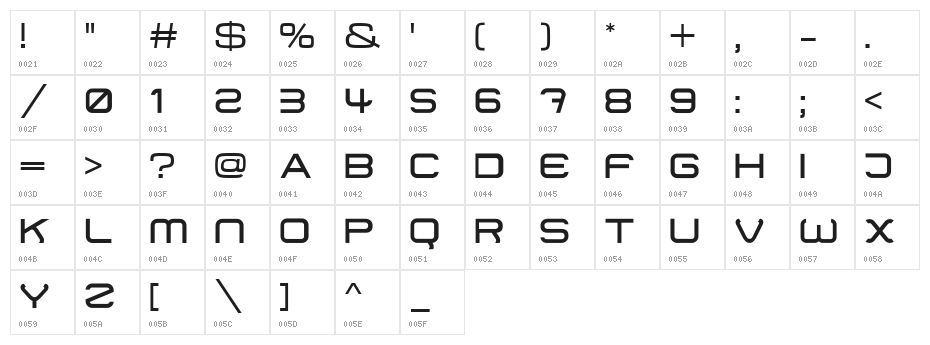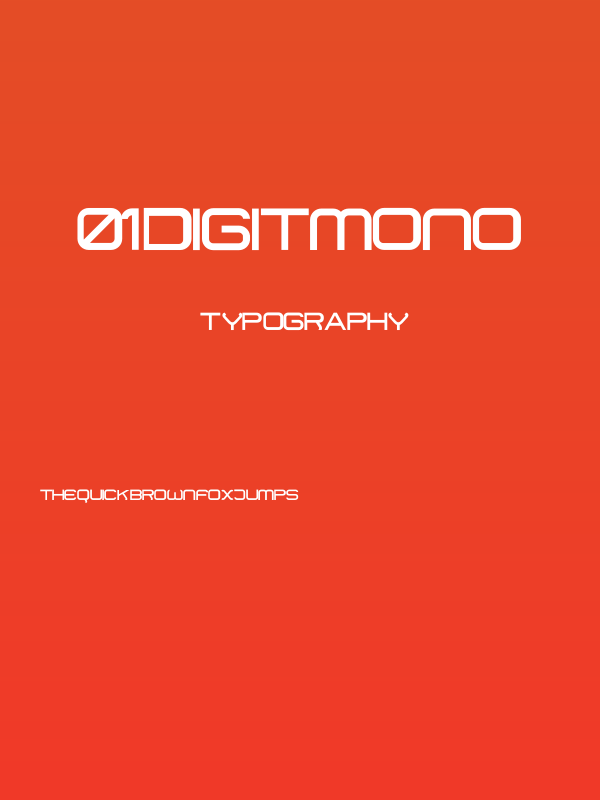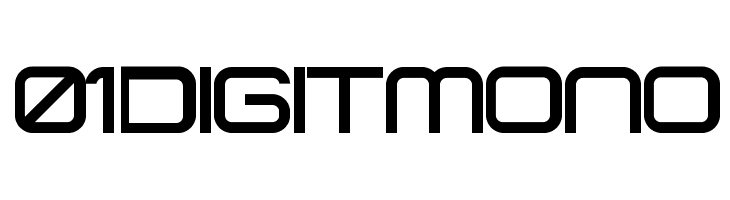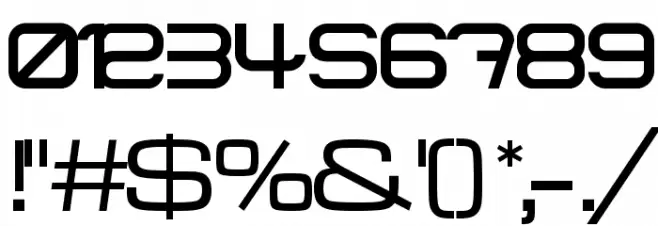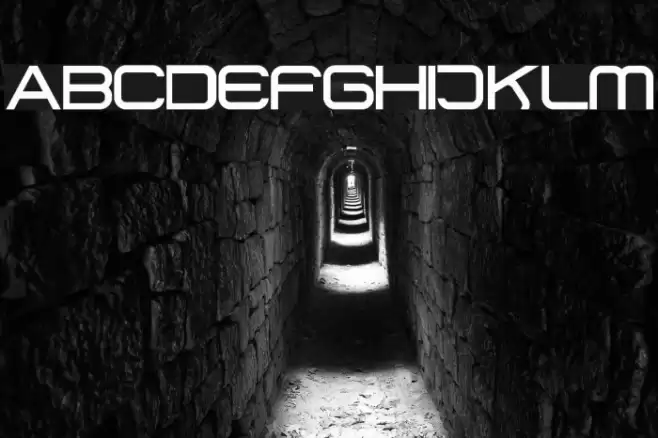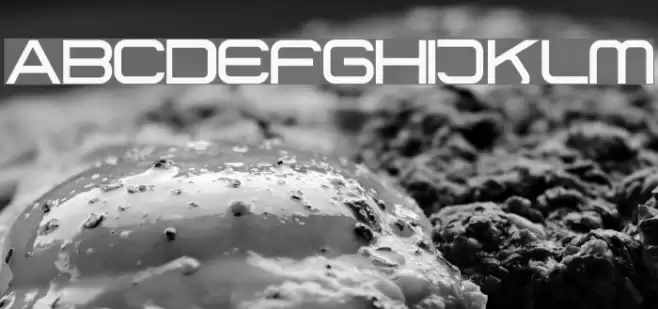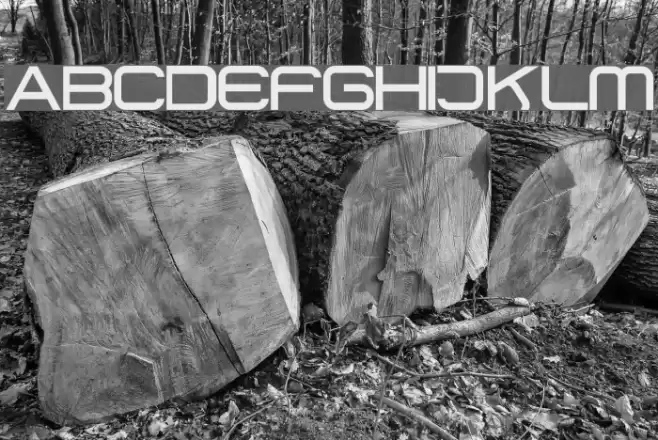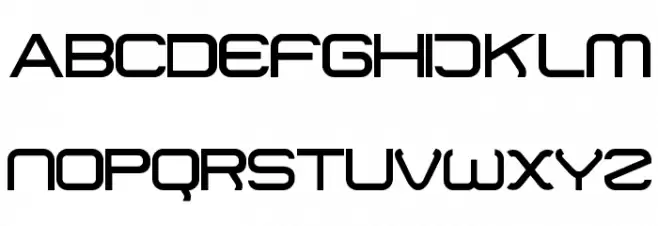
01 DigitMono Font
| حالة الاستخدام | Digital displays, technical documentation, coding. |
| مشاريع مقترحة | Ideal for digital interfaces, coding environments, technical documentation, and futuristic branding. |